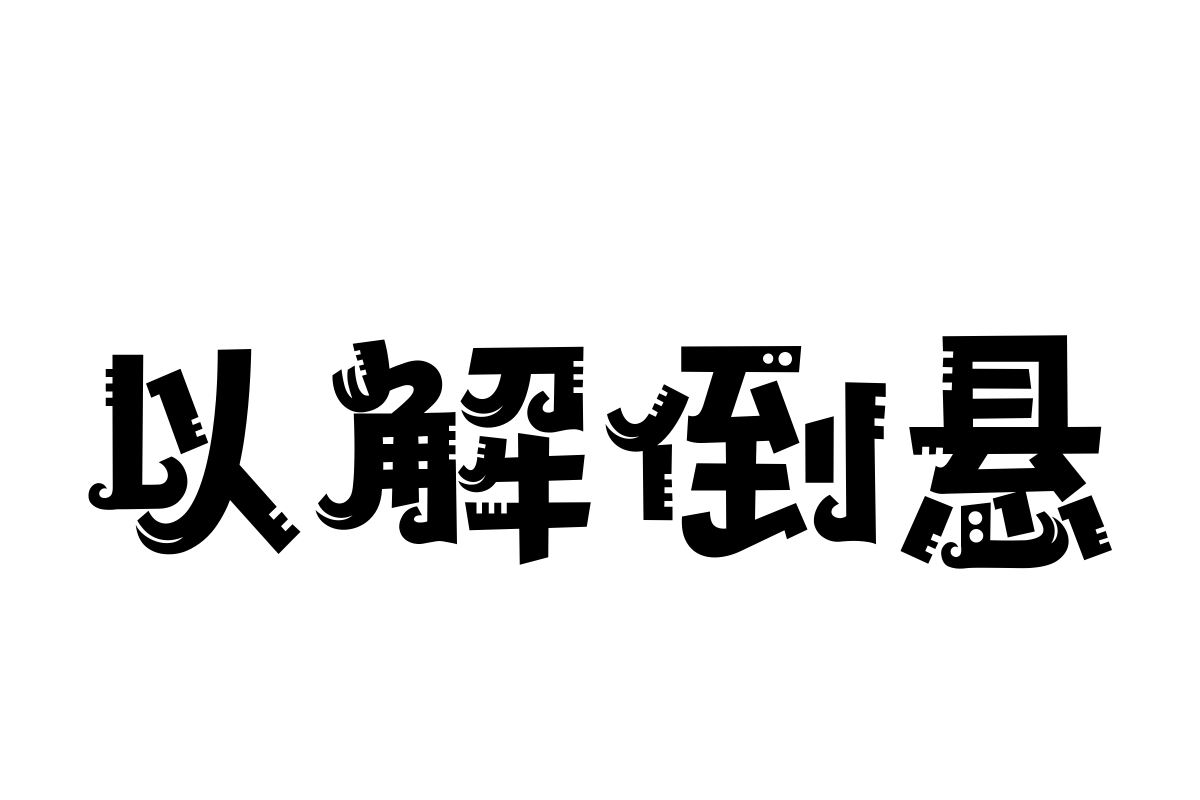
汉仪铸字马戏团是一款由汉仪公司开发的中文字体,具有独特的艺术风格和设计特点。这款字体以其流畅的线条、优雅的字形和丰富的表现力而受到广泛赞誉。
汉仪铸字马戏团的特点包括:
1. 独特性:汉仪铸字马戏团在字形设计上独具匠心,将传统的汉字与现代艺术元素相结合,创造出独特的视觉体验。
2. 流畅性:汉仪铸字马戏团的线条流畅自然,给人一种轻松愉悦的感觉。这种流畅性使得字体在各种应用场景中都能展现出良好的视觉效果。
3. 优雅性:汉仪铸字马戏团的字形结构优美,线条起伏有致,给人以优雅的美感。这种优雅性使得字体在设计作品中脱颖而出,具有较高的审美价值。
4. 可塑性:汉仪铸字马戏团的字形具有一定的可塑性,可以根据设计师的意图进行个性化调整。这使得字体在应用过程中更加灵活多变,能够满足不同场景的需求。
5. 适应性:汉仪铸字马戏团适用于多种应用场景,如广告、包装、印刷等。其独特的设计风格使得字体在各类媒体中都能够展现出良好的效果。
总之,汉仪铸字马戏团是一款具有独特艺术风格的中文字体,其流畅的线条、优雅的字形和丰富的表现力为设计作品增添了一份独特的魅力。